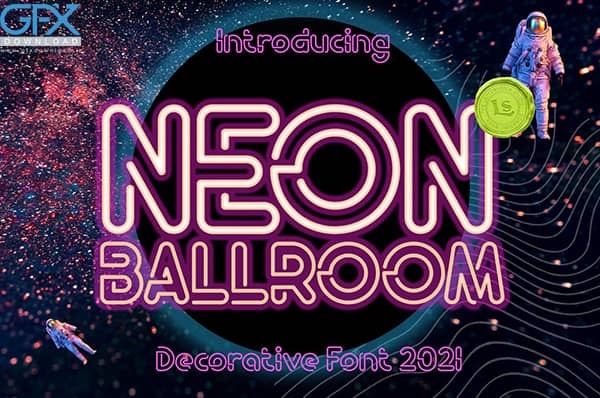
دانلود فونت نئون دار Neon Ballroom
دانلود فونت با افکت نئون Neon Ballroom
دانلود فونت نئون دار Neon Ballroom یکی از زیباترین و جدیدترین فونت های حرفه ای با استایل نئون می باشد که طراحی بی نظیر و جذاب آن می تواند توجه بیننده را به خود جلب کند. این فونت جذاب الهام گرفته شده در یک کافه قدیمی است. مقداری دستخط طبیعی به آن اضافه شده است تا یک احساس طبیعی ساخته شده به هویت آن اضافه کند. ویژگی های این فونت نئون دارای 203 کاراکتر است. این فونت برای مواردی از جمله آرم ، برچسب ، بسته بندی محصول ، دعوت نامه ، تبلیغات و موارد دیگر بسیار زیبا به نظر می رسد.
دانلود فونت نئونی Neon Ballroom
دانلود فونت زیبا با طرح نئون دار Neon Ballroom